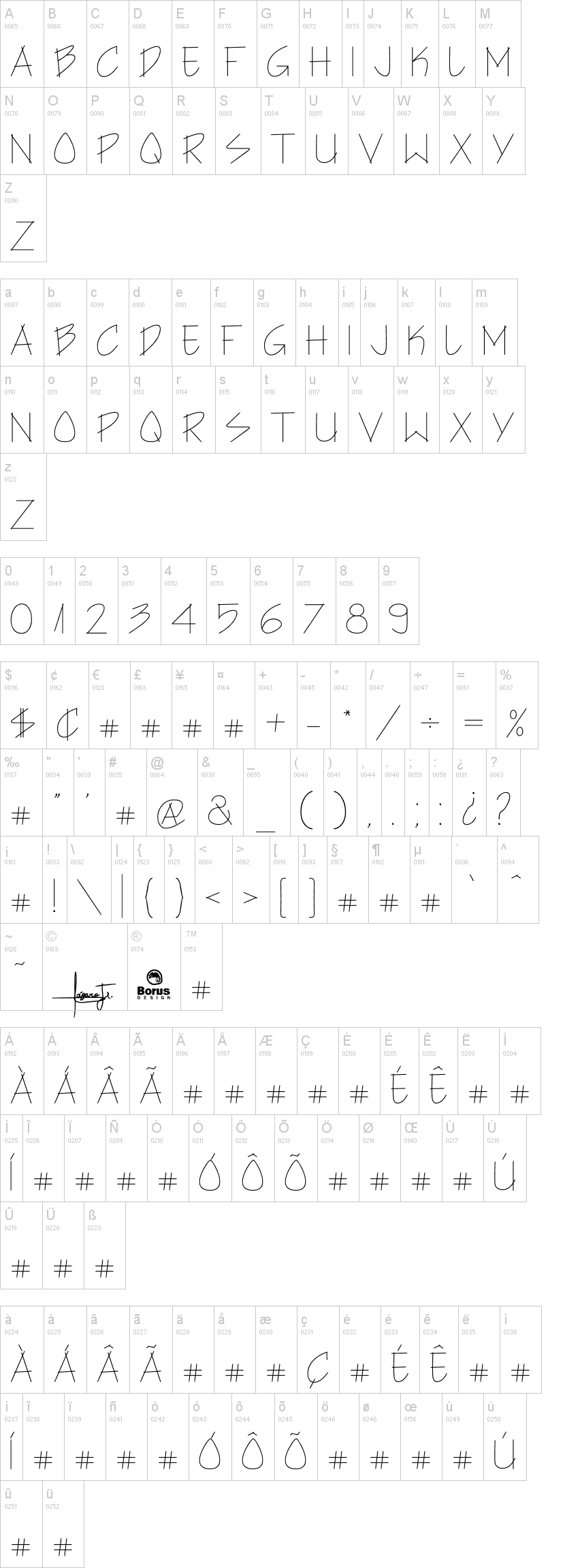
Шрифт Architect's Hand
A fonte Architect´s Hand foi criada para atender de forma digital, a tipologia usada por Arquitetos e Engenheiros que faziam as descrições dos projetos a mão. Através das normas da ABNT, seguindo rigorosamente sua característica padrão.